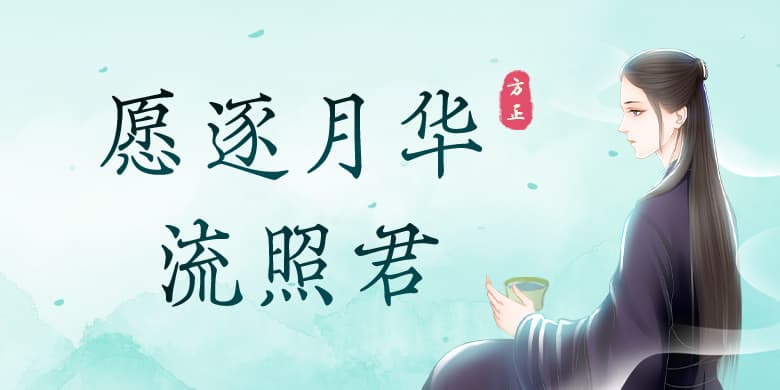
方正手迹-愿逐月华流照君
品牌:方正手迹设计师:余丹发行时间:2020字库编码:大陆简体(GB2312-80)分类:常规书写·硬笔字体属性:精品字
方正手迹-愿逐月华流照君
愿逐月华流照君是一款潇洒的手写体。该字体整体结构稳定,笔画坚实有力,舒展优雅。适用于文艺类的书刊、品牌广告和产品包装设计,以及社交网络的个性化用字。